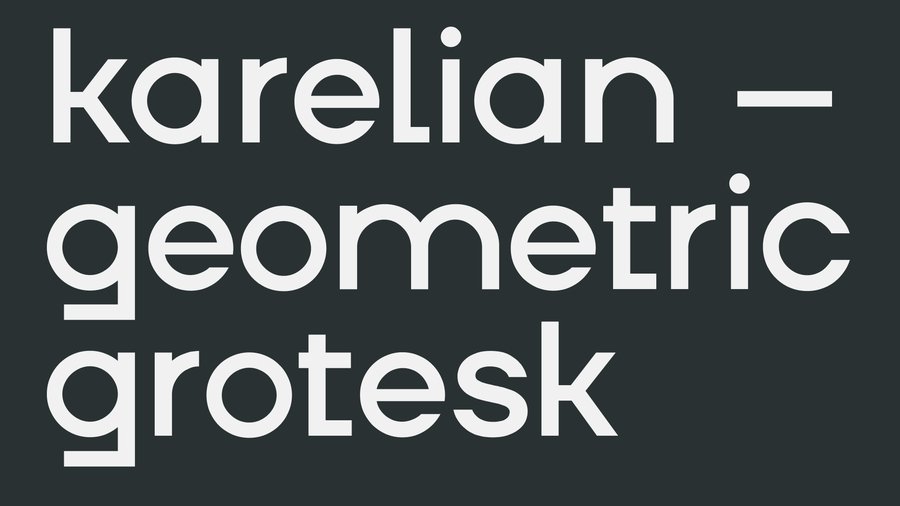
Шрифт и айдентика для ювелирной студии
Студия Ксении Кошкиной — это необычная ювелирная студия, в которой есть уникальные секретные туры за гранатами, альмандинами и аметистами на русский север, авторские мастер-классы и архитектурно-чувственные, тактильные украшения из серебра с полудрагоценными камнями.
Основой стиля стал вдохновленный карельской вышивкой, винтажными восточноевропейскими и русскими течениями и тенденциями, строгим севером — karelian font. Это стильный геометрический гротеск со своим характером, а сильные линии, жесткие углы и полукруги придают ему индивидуальности
Фирменный стиль также отсылает
на карелию, как вечное вдохновение создательницы и одну из уникальных особенностей студии. Так виды, характерные для карелии, легли
в основу цветов бренда, фотографии переняли туманность, а характер этого края в сочетании с инициалами создательницы отразился в знаке